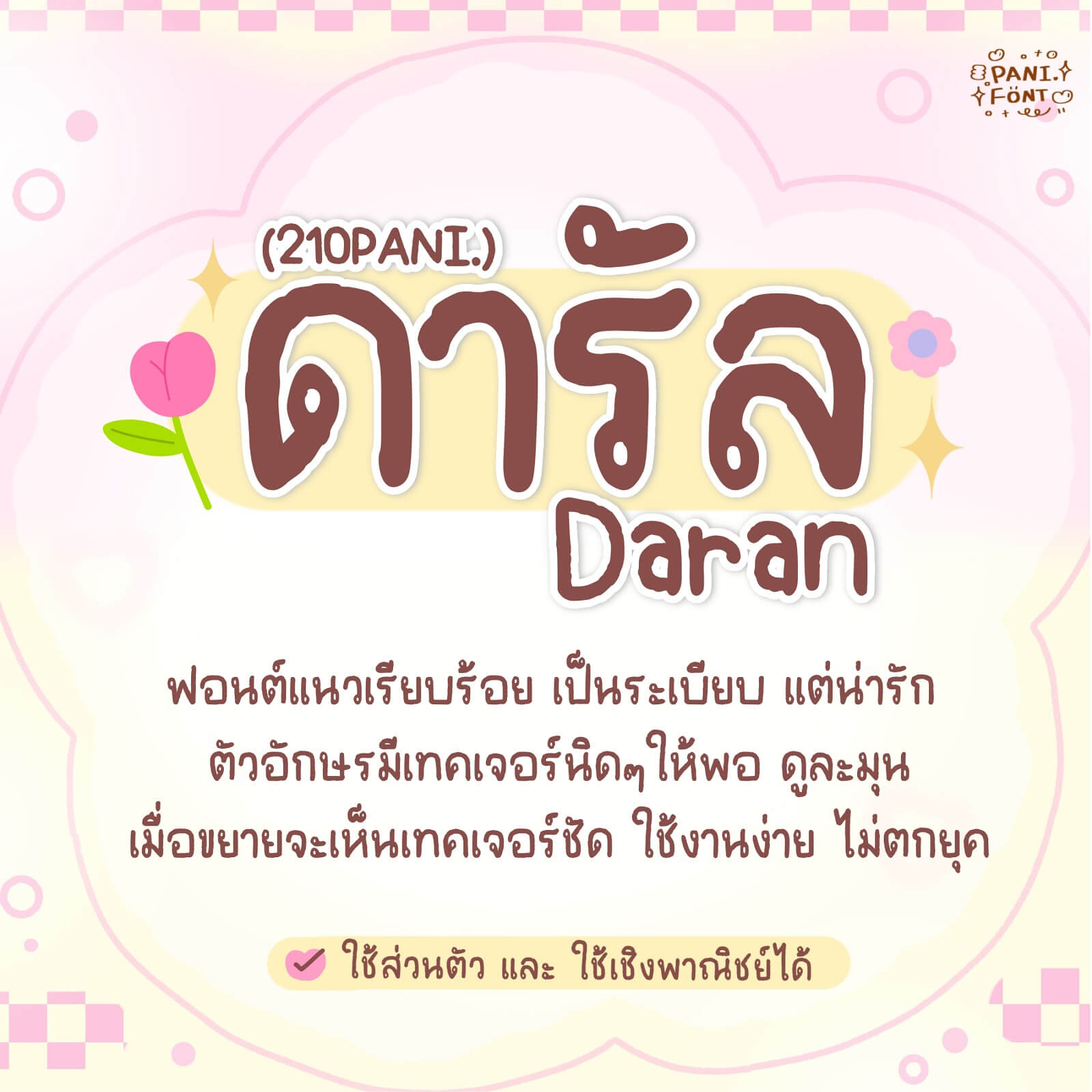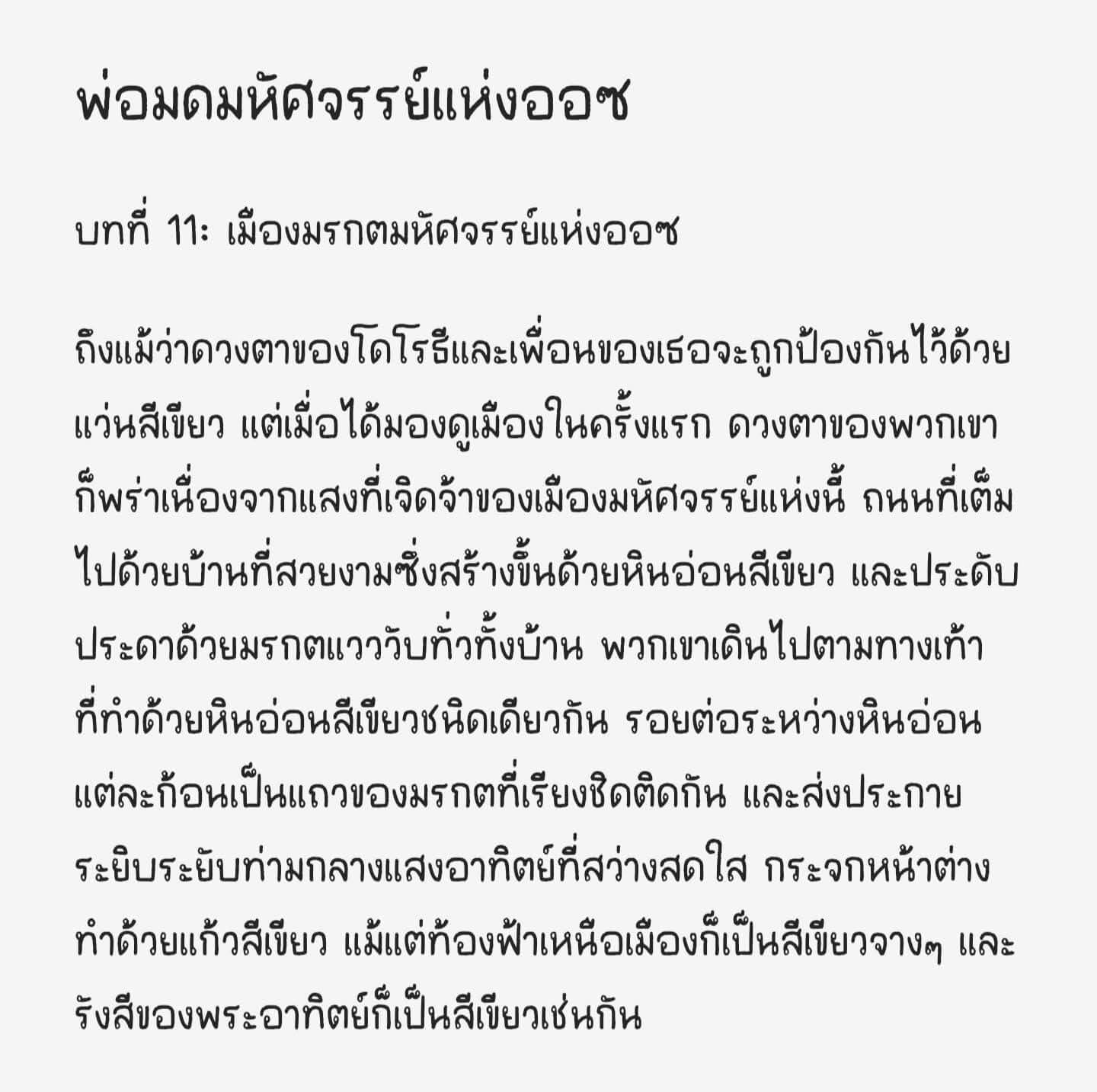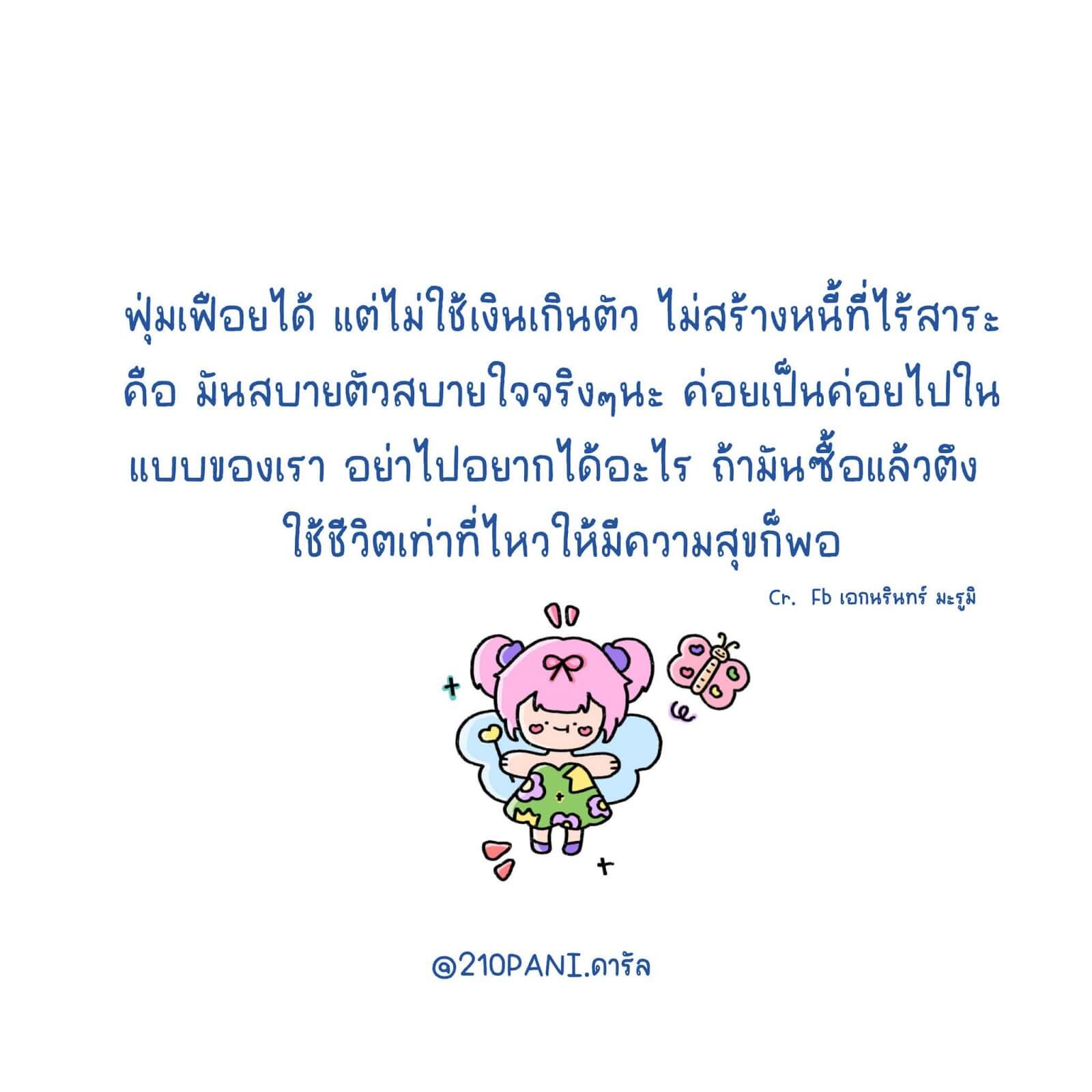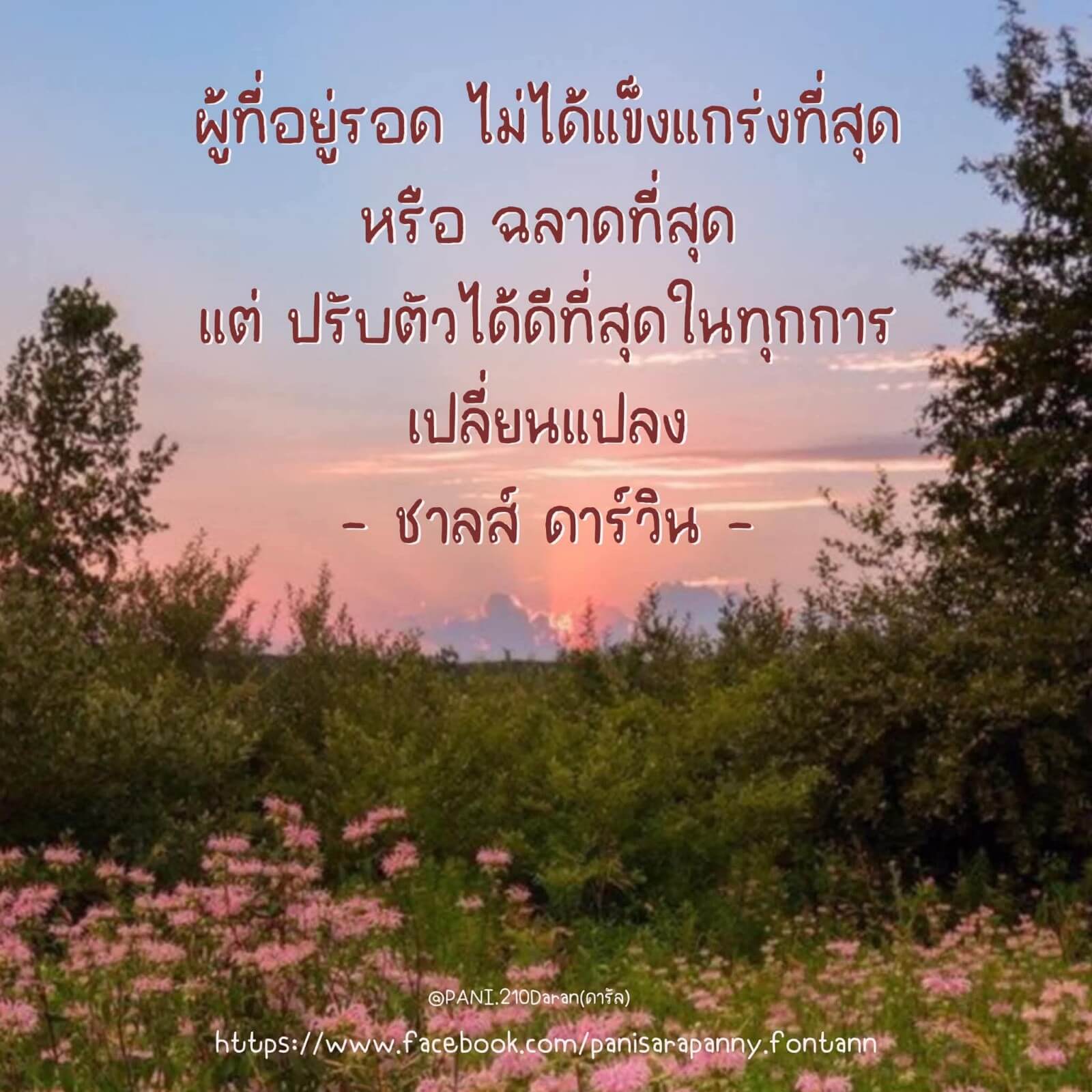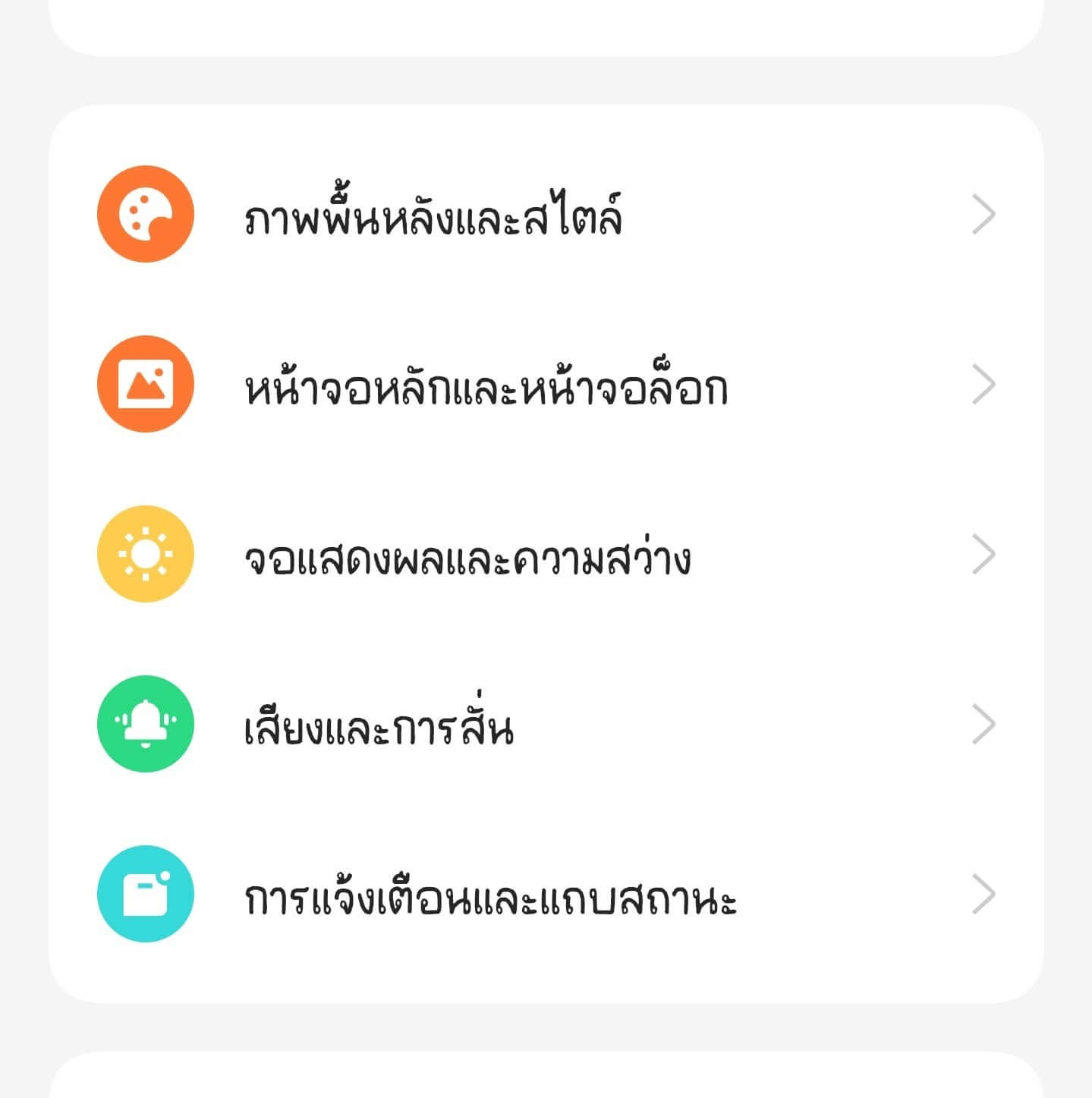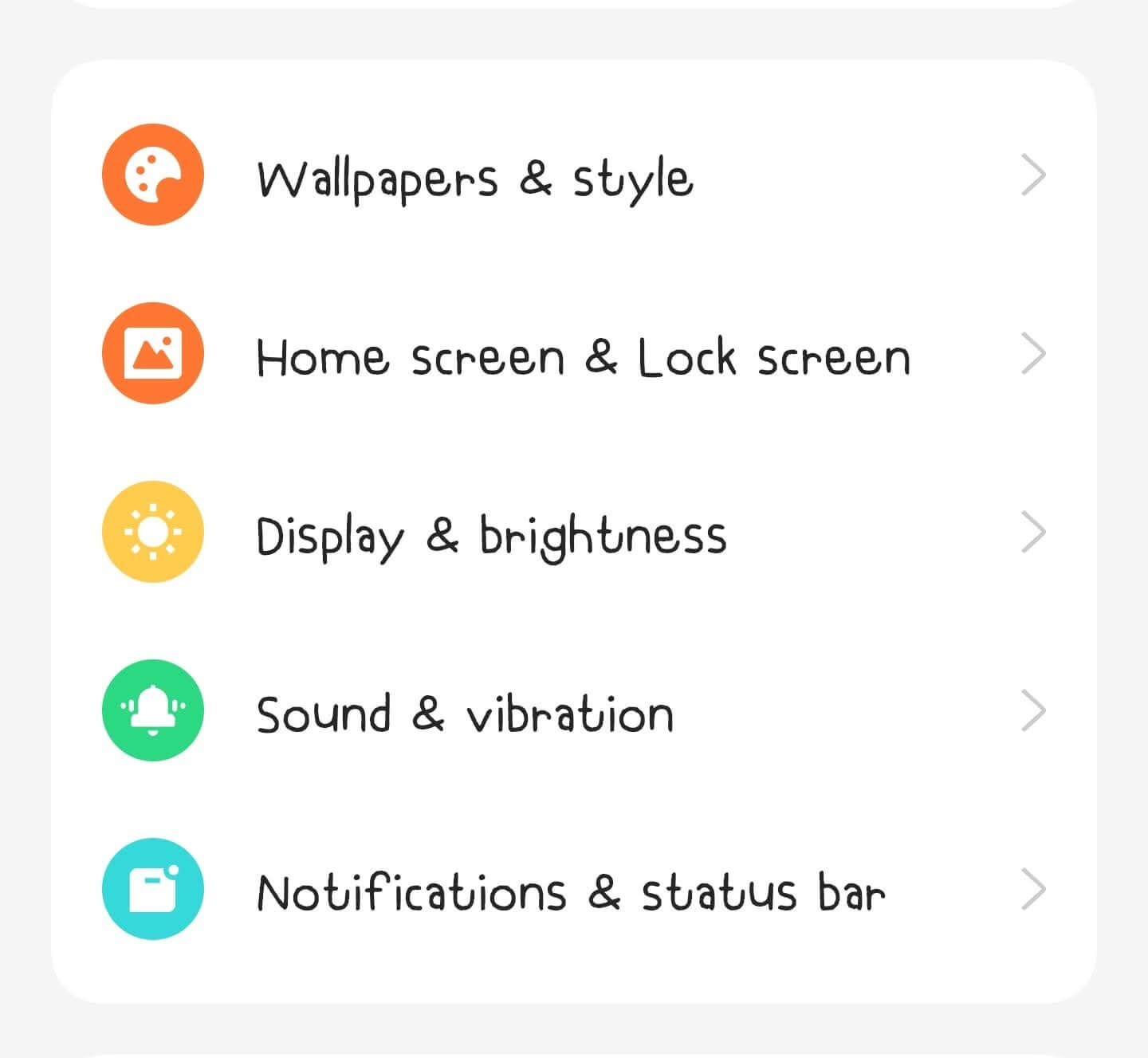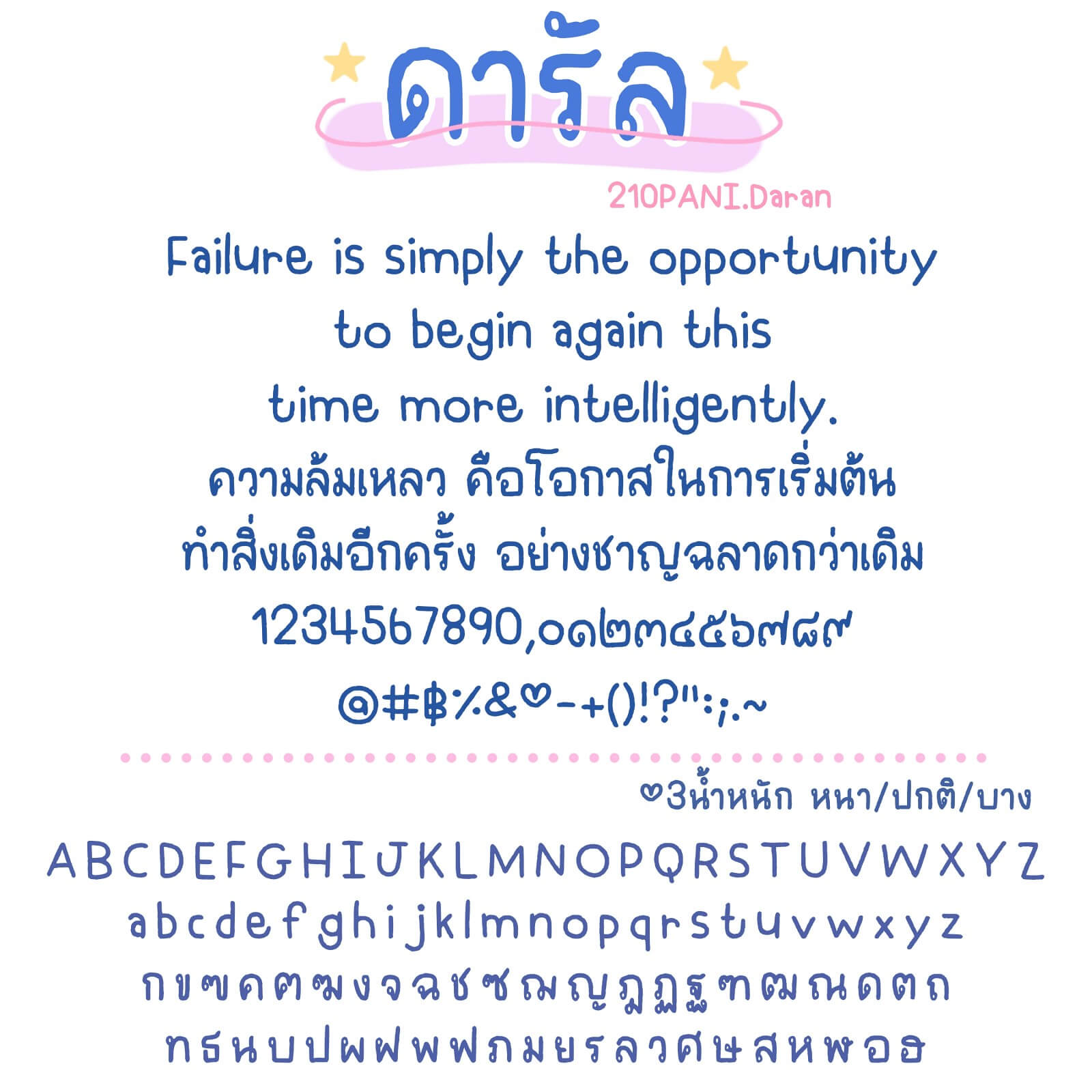
ฟอนต์ 210PANI.ดารัล – ฟอนต์แนวเรียบร้อย เป็นระเบียบ แต่น่ารัก ตัวอักษรมีเท็กซ์เจอร์นิดๆ ให้พอดูละมุน เมื่อขยายจะเห็นเท็กซ์เจอร์ชัด ใช้งานง่าย ไม่ตกยุค
210PANI.ดารัล